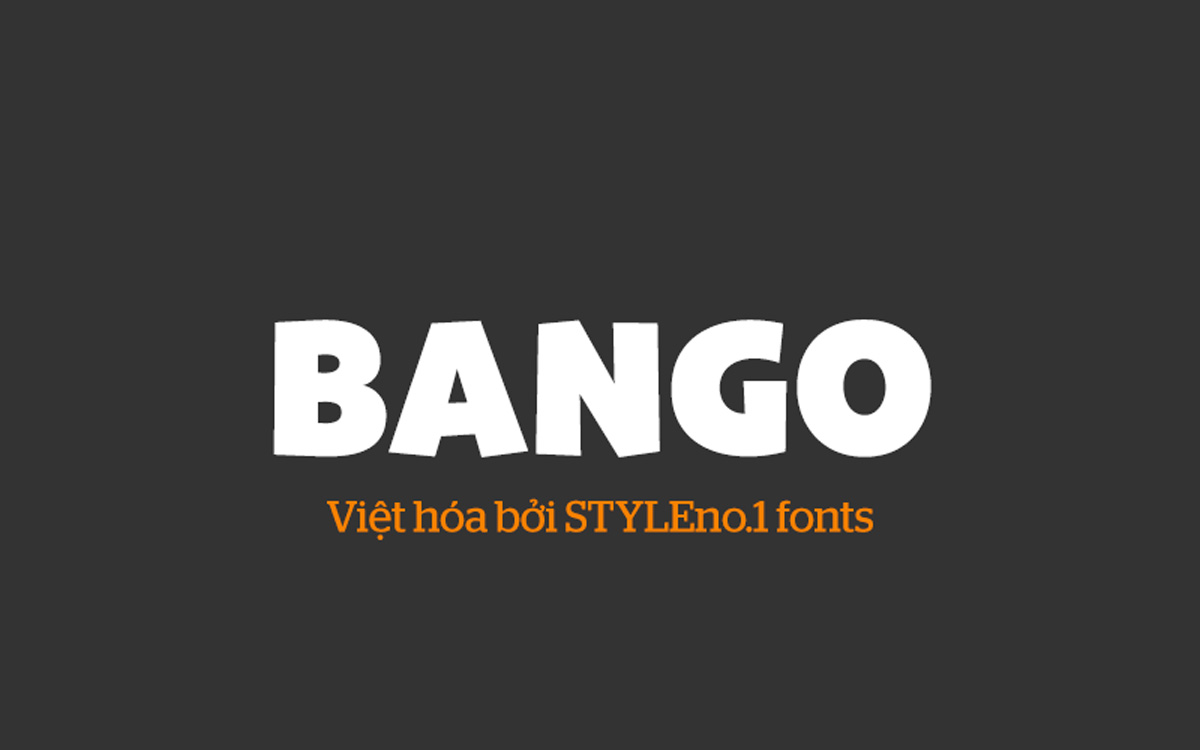
Trong thế giới thiết kế đồ họa sáng tạo, việc lựa chọn bộ phông chữ phù hợp đóng vai trò quyết định đến cảm xúc và sự chú ý của khách hàng mục tiêu. SVN Bango nổi lên như một giải pháp typography hoàn hảo, mang đậm phong cách vui tươi, ngộ nghĩnh và đầy sức sống. Được tối ưu hóa chuyên biệt cho các dự án thiết kế hướng đến trẻ em và ngành hàng ẩm thực (F&B), font chữ này hứa hẹn sẽ thổi một làn gió mới, biến mọi ấn phẩm truyền thông trở nên vô cùng sinh động và hấp dẫn.
Khám Phá SVN Bango – Font Chữ Vui Vẻ, Dễ Thương, Hoạt Hình Đỉnh Cao Cho Lĩnh Vực Trẻ Em Và Đồ Ăn Cute
Để tạo nên một sản phẩm thiết kế có sức hút thị giác mạnh mẽ, các nhà thiết kế luôn tìm kiếm những phông chữ không chỉ đẹp mà còn phải truyền tải đúng tinh thần thương hiệu. Font chữ SVN Bango được Việt hóa trọn bộ, giữ nguyên nét cá tính nguyên bản kết hợp với sự tinh chỉnh hoàn hảo cho ngôn ngữ tiếng Việt. Với nét chữ béo tròn, các đường cong mềm mại cùng khoảng hở ngộ nghĩnh, SVN Bango đã trở thành sự lựa chọn hàng đầu cho các nhà sáng tạo nội dung, agency quảng cáo và các chủ doanh nghiệp đang muốn xây dựng hình ảnh thương hiệu thân thiện, gần gũi.
Dù bạn đang thiết kế bảng hiệu cho một quán trà sữa cute, bao bì đồ ăn vặt, hay xây dựng bộ nhận diện cho thương hiệu đồ chơi trẻ em, SVN Bango đều đáp ứng xuất sắc các tiêu chí về thẩm mỹ và khả năng ứng dụng thực tế. Hãy cùng điểm qua những đặc điểm nổi bật khiến bộ font này luôn giữ vị trí “top trending” trong cộng đồng designer hiện nay.
1. Phong Cách Thiết Kế Béo Tròn, Ngộ Nghĩnh Và Đậm Tính Hoạt Hình
Điểm đặc trưng đầu tiên khiến SVN Bango ghi điểm tuyệt đối chính là kiểu dáng chữ display (chữ hiển thị) đầy ấn tượng. Font chữ sở hữu nét bút dày (bold heavy), kết hợp với các góc bo tròn được xử lý khéo léo, loại bỏ hoàn toàn sự thô cứng của các phông chữ truyền thống.
- Đường nét ngẫu hứng: Các nét chữ không hoàn toàn tuân theo quy tắc đối xứng gắt gao mà có sự biến tấu nhẹ nhàng, gợi liên tưởng đến những chữ viết tay trong các cuốn truyện tranh hay phim hoạt hình kinh điển.
- Sự cân bằng thị giác: Dù sở hữu nét chữ siêu mập mạp, các khoảng trống bên trong ký tự (counter) vẫn được sắp xếp hợp lý, giúp font chữ giữ được độ thông thoáng, không bị dính nét hay gây rối mắt khi nhìn từ xa.
- Cảm xúc tích cực: Hình dáng tròn trịa tự nhiên tỏa ra năng lượng của sự vui vẻ, hòa đồng, kích thích sự tò mò của trẻ em và tạo cảm giác ngon miệng cho các tín đồ ẩm thực.
2. Hỗ Trợ Việt Hóa Hoàn Chỉnh Với Bộ Glyph Đa Dạng
Một trong những rào cản lớn nhất của các designer Việt Nam khi sử dụng phông chữ nước ngoài là lỗi font tiếng Việt hoặc các dấu thanh (sắc, huyền, hỏi, ngã, nặng) bị lệch tông, mất thẩm mỹ. Bản Việt hóa SVN Bango đã giải quyết triệt để vấn đề này.
Bộ font được chăm chút kỹ lưỡng từng dấu thanh, đảm bảo độ cao, độ nghiêng và tỉ lệ hài hòa tuyệt đối với các ký tự Latinh gốc. Hệ thống dấu tiếng Việt được thiết kế cách điệu nhẹ nhàng, giữ trọn nét dễ thương mà không làm mất đi tính rõ ràng của văn bản. Ngoài ra, SVN Bango còn tích hợp đầy đủ các ký tự đặc biệt, dấu câu, chữ số và biểu tượng thông dụng, giúp quá trình thao tác trên các phần mềm đồ họa như Adobe Photoshop, Illustrator, InDesign hay Canva trở nên vô cùng thuận tiện.
3. Giải Pháp Typography Hoàn Hảo Cho Ngành Thực Phẩm Và Đồ Uống (F&B)
Trong ngành F&B, yếu tố visual (hình ảnh) quyết định đến 80% hành vi mua hàng của khách hàng, đặc biệt là giới trẻ và Gen Z. SVN Bango chính là “vũ khí bí mật” giúp các thương hiệu đồ ăn, thức uống bứt phá:
- Thiết kế Menu & Thực đơn: Các tiêu đề món ăn sử dụng SVN Bango sẽ ngay lập tức nổi bật, tạo cảm giác hấp dẫn, ngon lành và kích thích vị giác của thực khách.
- Bao bì sản phẩm: Phù hợp hoàn hảo cho các mẫu hộp bánh, túi trà sữa, hũ kẹo, chai nước trái cây, bao bì đồ ăn vặt nội địa. Sự cute của font chữ khiến bao bì trở nên vô cùng “Instagrammable”, dễ dàng được khách hàng chụp ảnh check-in.
- Bảng hiệu & Trang trí cửa hàng: Tạo nên điểm nhấn thương hiệu độc đáo, biến không gian quán trở nên thân thiện và tràn ngập không khí lễ hội, tươi vui.
4. Lựa Chọn Số 1 Cho Các Dự Án Giáo Dục, Thời Trang Và Sản Phẩm Trẻ Em
Trẻ em luôn bị thu hút bởi những hình ảnh có màu sắc rực rỡ và hình dáng bo tròn ngộ nghĩnh. SVN Bango đáp ứng chính xác tâm lý học thị giác này của độ tuổi thiếu nhi.
Các nhà xuất bản có thể ứng dụng font chữ này làm tiêu đề cho sách truyện thiếu nhi, bìa tập tô màu, hay bảng chữ cái giáo dục. Đối với mảng thời trang và đồ chơi, SVN Bango cực kỳ thích hợp để in lên áo phông em bé, nhãn mác sản phẩm, biển hiệu trường mầm non hay các khu vui chơi giải trí. Nét chữ tựa như những khối đất nặn sáng tạo sẽ giúp các bé cảm thấy gần gũi, kích thích trí tưởng tượng phong phú.
5. Tối Ưu Hóa Hiển Thị Trên Cả Nền Tảng Kỹ Thuật Số Và Ấn Phẩm In Ấn
Không chỉ phát huy tác dụng trên các ấn phẩm in ấn thực tế như poster, banner, standee hay flyer, SVN Bango còn cho khả năng hiển thị vượt trội trên môi trường kỹ thuật số. Nhờ cấu trúc nét chữ dày và rõ ràng, phông chữ này giữ nguyên độ sắc nét khi xuất hiện trên màn hình điện thoại, máy tính bảng hay màn hình LED ngoài trời.